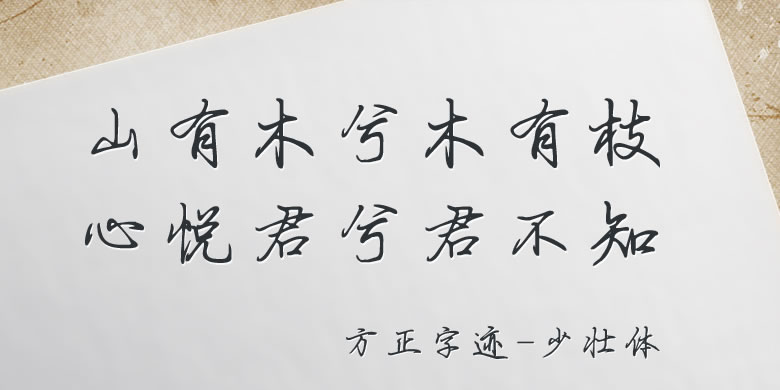
品牌:方正字迹设计师:罗源森发行时间:2017字库编码:大陆简体(GB2312-80)、大陆繁体(GB12345-90)分类:常规书写·硬笔
“小书法家”罗源森,2004年生人,现年只有14岁。自幼酷爱书法,四岁起随父亲罗心海学习柳体《玄秘塔碑》、欧体《九成宫碑》和魏碑《等慈寺碑》,学前就打下了扎实的正书根基,六岁开始学习硬笔,八岁学习行书,被学校老师和同学们誉为“小书法家”。
作者在父亲的指导下,大胆运用毛笔柳体中的方刚果敢,魏碑中的沉劲雄浑,欧体中的险峻,王羲之《兰亭序》的行云流水,清秀飘逸,米芾书法中的险、绝、侧、倾的体势等风格,把这些妙法融合到硬笔行书当中,结合规范汉字的书写要求,创作出了这套硬笔书法字库。